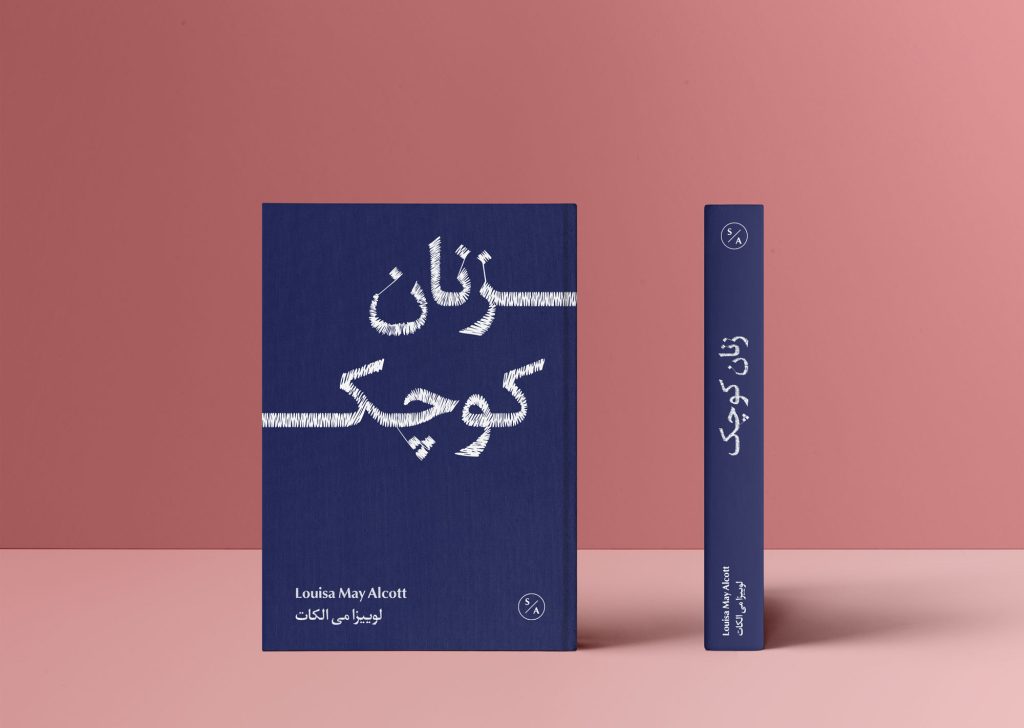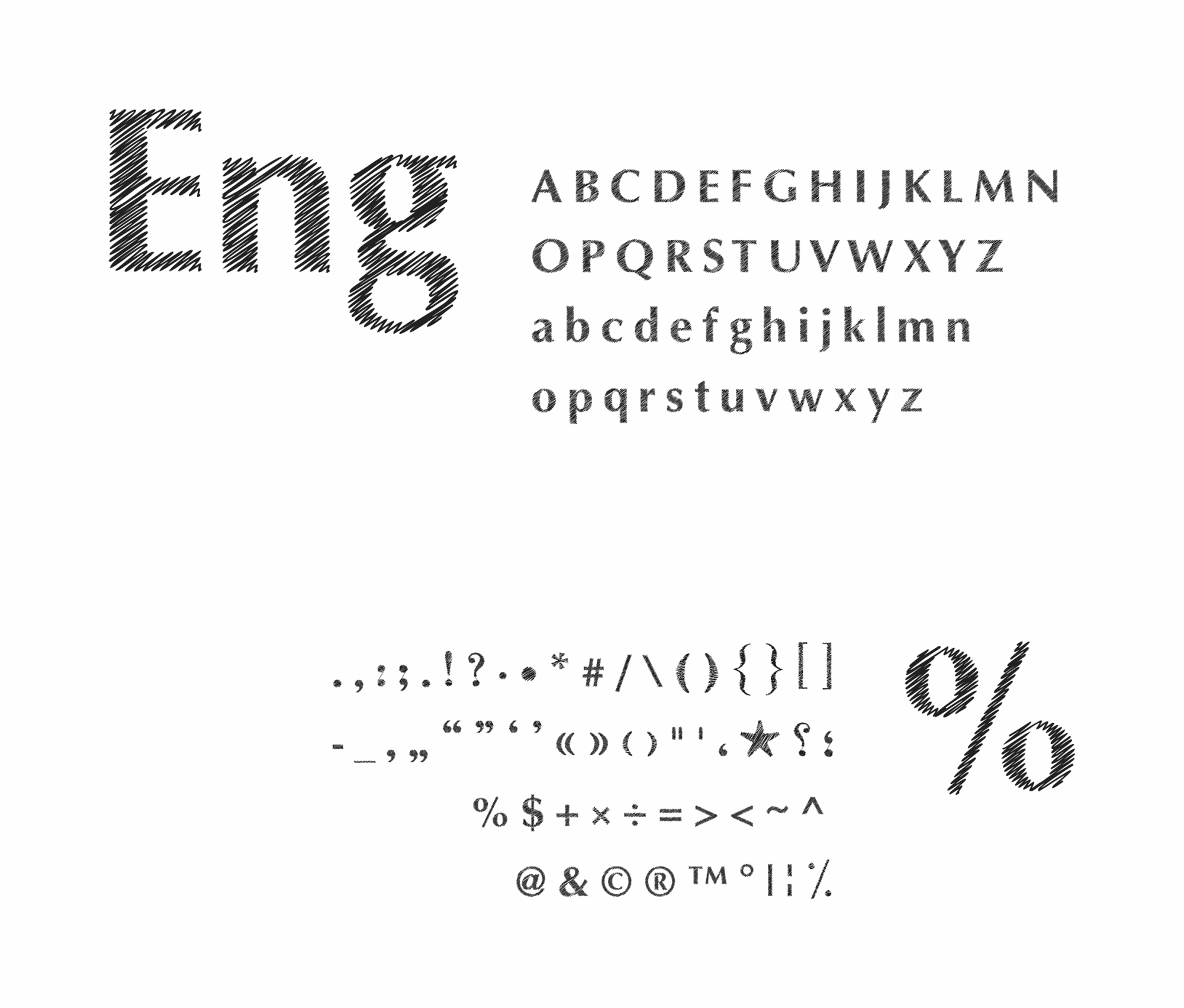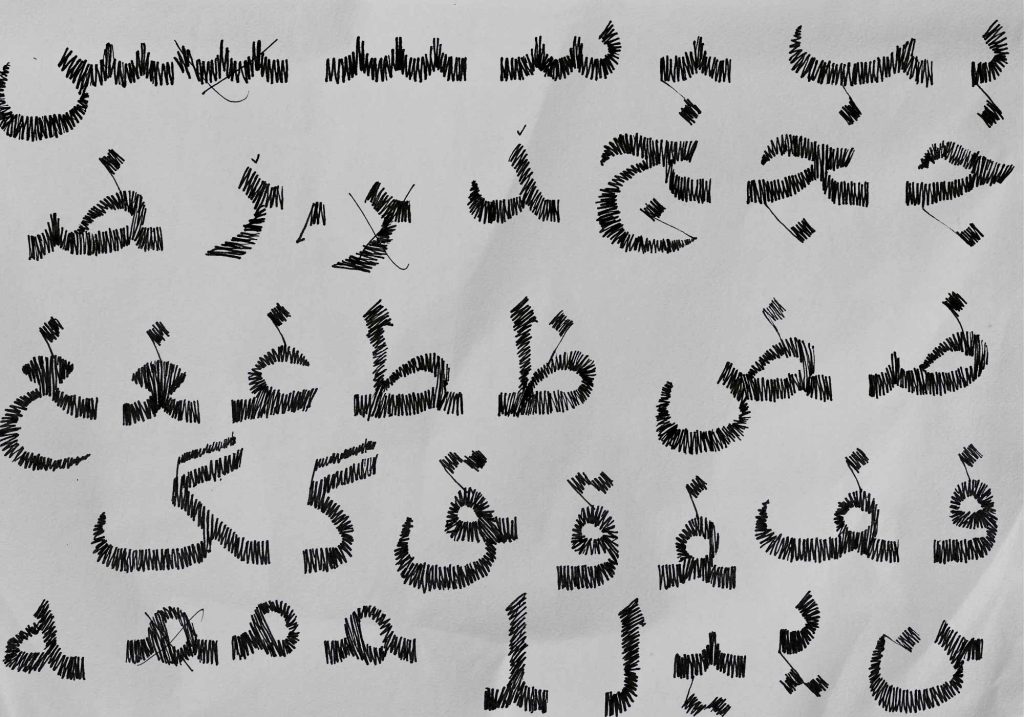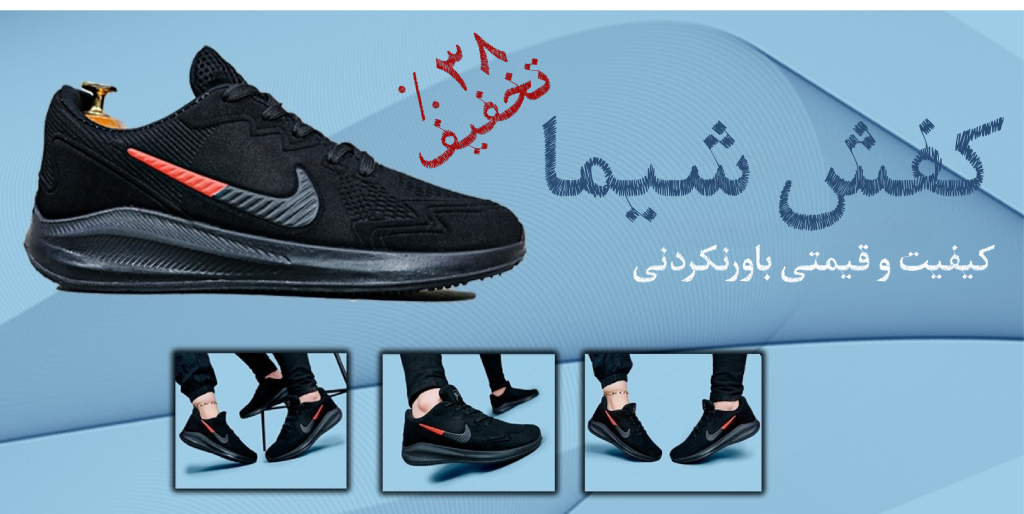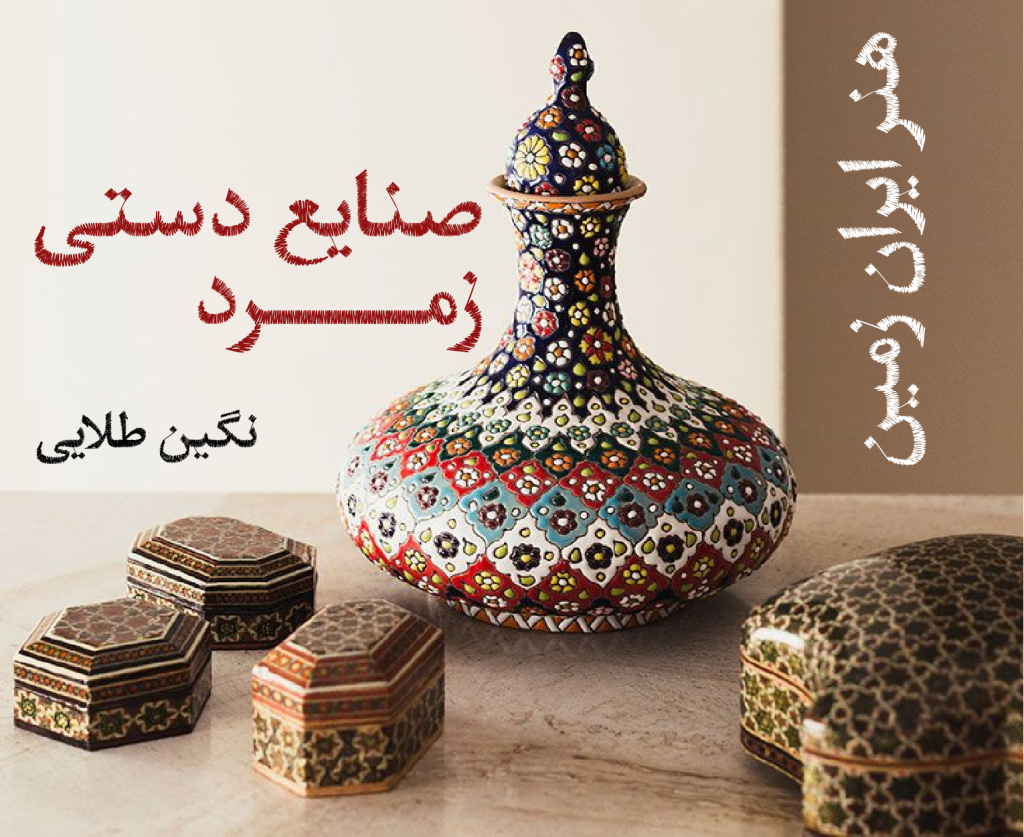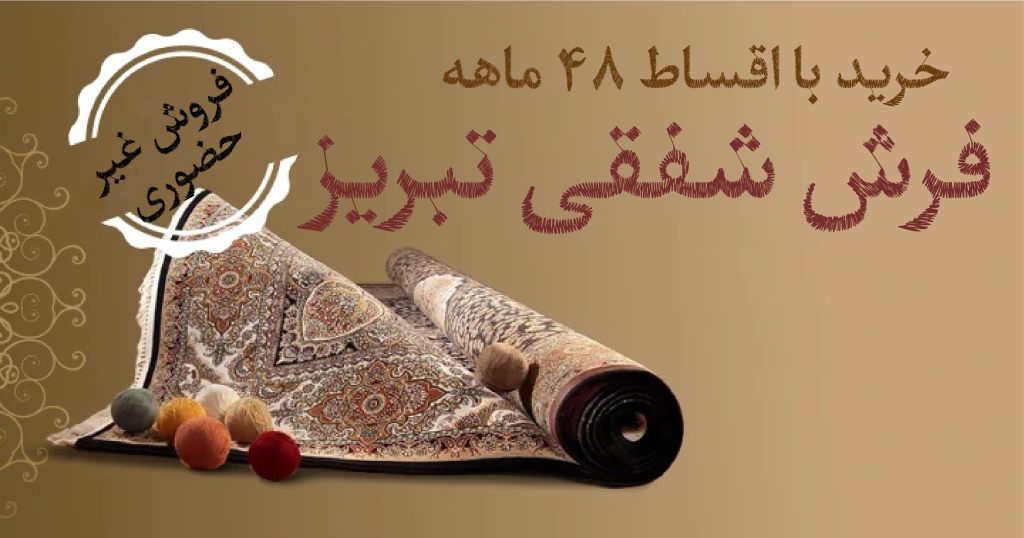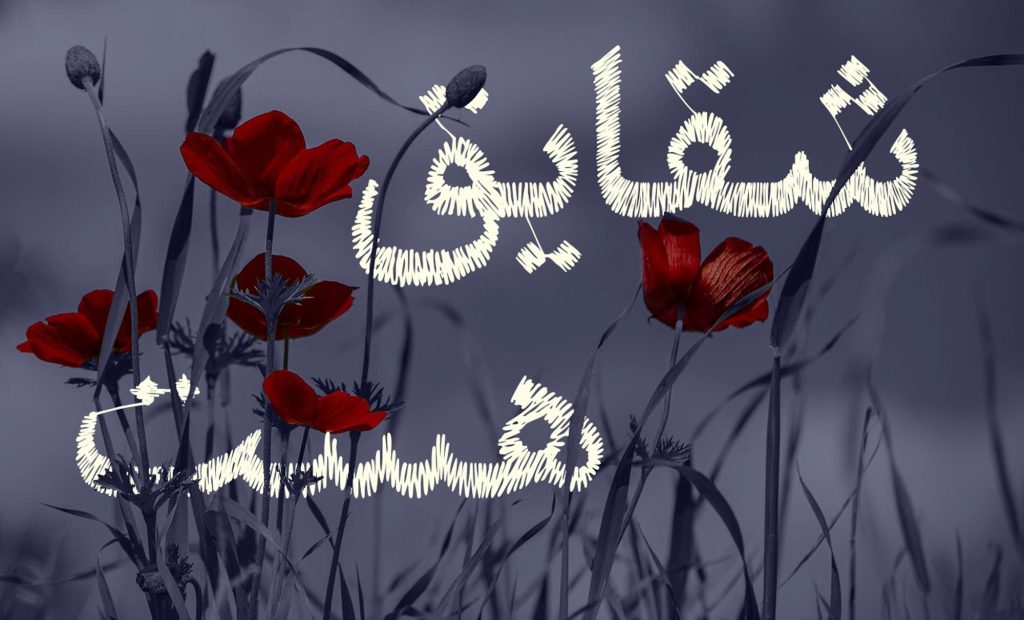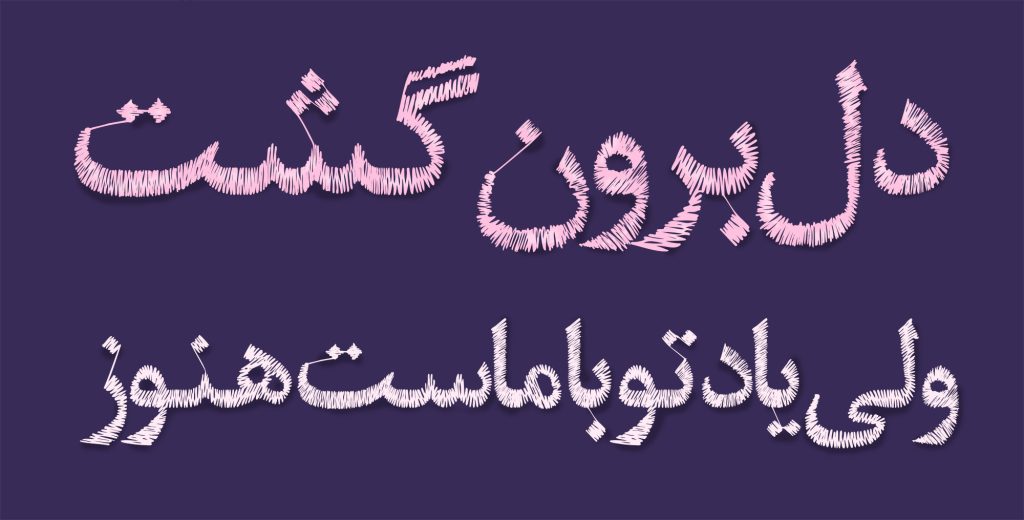
فونت پرنیان قلمی که بر روی فونت زیبای نازنین ساختار تزئینی و نمایشی را ایجاد نموده تا بر ویژگی نمایشی و جذابیت آن بیفزاید . با ما همراه باشید.
فونت پرنیان
فونت پرنیان قلمی ویژه با سبک طراحی نو و جدید با هدف افزایش جاذبه های بصری طرح و نگاره گلدوزی را بر روی تایپ فیس نام آشنا و مشهور نازنین انجام داده است. این پیاده سازی و ایده طراحی توسط طراحان آن در کارگاه طراحی تایپ آقای مسلم ابراهیمی در سایت مرجع فونت ایران انجام گردیده است.
پرنیان قلمی نمایشی و تزئینی
این قلم در ابتدا کار به صورت دستی پیاده سازی و سپس با کمک شبیه سازی رایانه و گرفتن تصاویری حرکت نخ گلدوزی در آن پیاده سازی شده است. پرواضح است که پیاده سازی طرح گلدوزی شبیه سازی شده که تزئین و نمایشی زیبا و جذاب است نگاه مخاطبان و بینندگان را به خود می کشاند و عنصر نمایشی فوق العاده و اغراق آمیزی به این قلم می بخشد. همانطور که می دانید تایپ فیس های نمایشی مناسب استفاده در اندازه‌های بزرگ هستند همانند متون کوتاه و تیتر های مطبوعاتی و تبلیغاتی هستند .
پرنیان دارای شخصیتی پویا و پر انرژی می باشد که می تواند در جذب نگاه بینندگان به متون و عناوین شما بهترین انتخاب باشد. در زیر تصاویری از این قلم ویژه و خاص را می توانید مشاهده کنید.